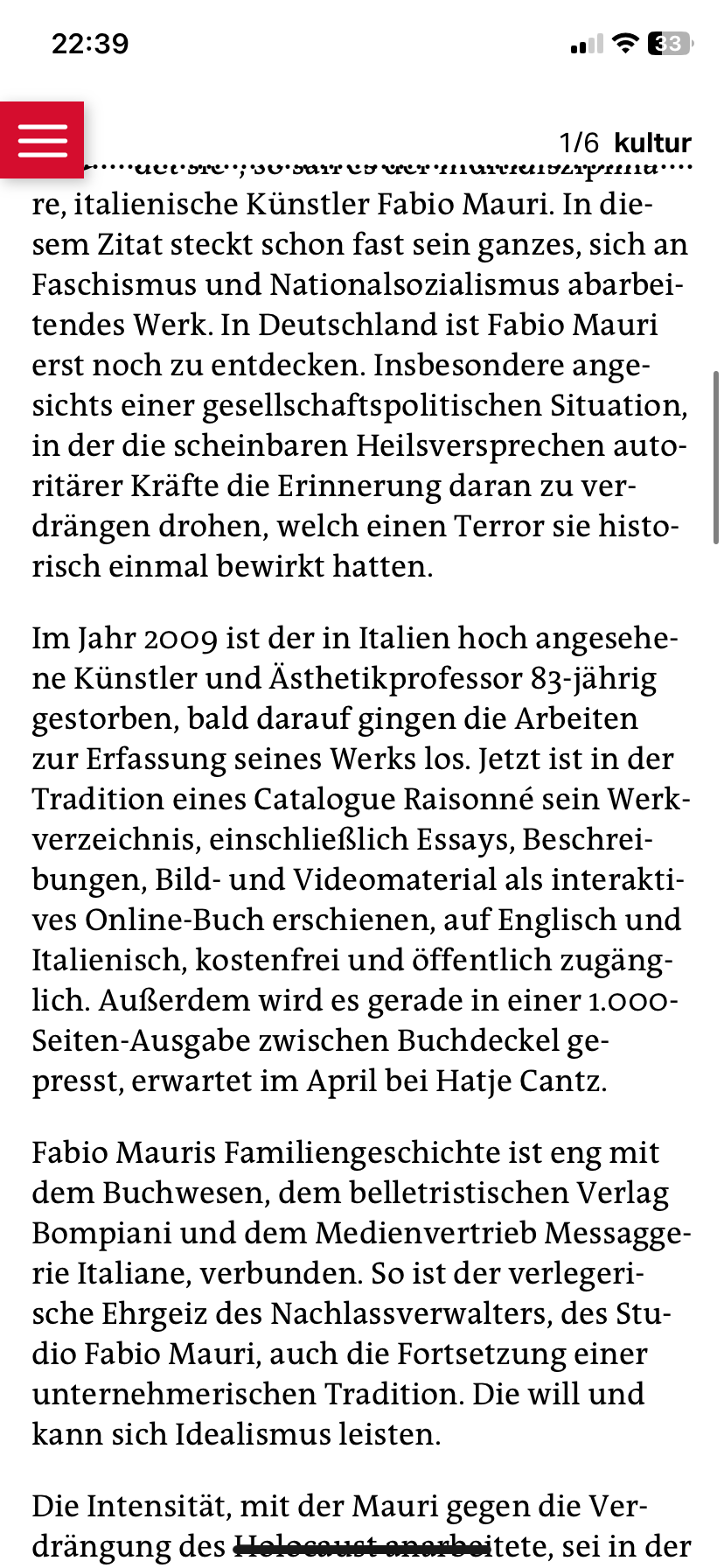
QuaText - da stimmt doch was nicht?
Ich kann mir nicht helfen, die QuaText, die mir als Mengentext bei der TAZ App angezeigt wird, sieht für mich nicht in Ordnung aus: Laufweite zu luftig, dafür der Zeilenabstand zu gering. Ein Text, den ich sehr gerne „flüssig“ lesen möchte, bröckelt Buchstabe für Buchstabe vor sich hin …
Kann mir jemand helfen? Ist an meiner Sichtweise was dran?